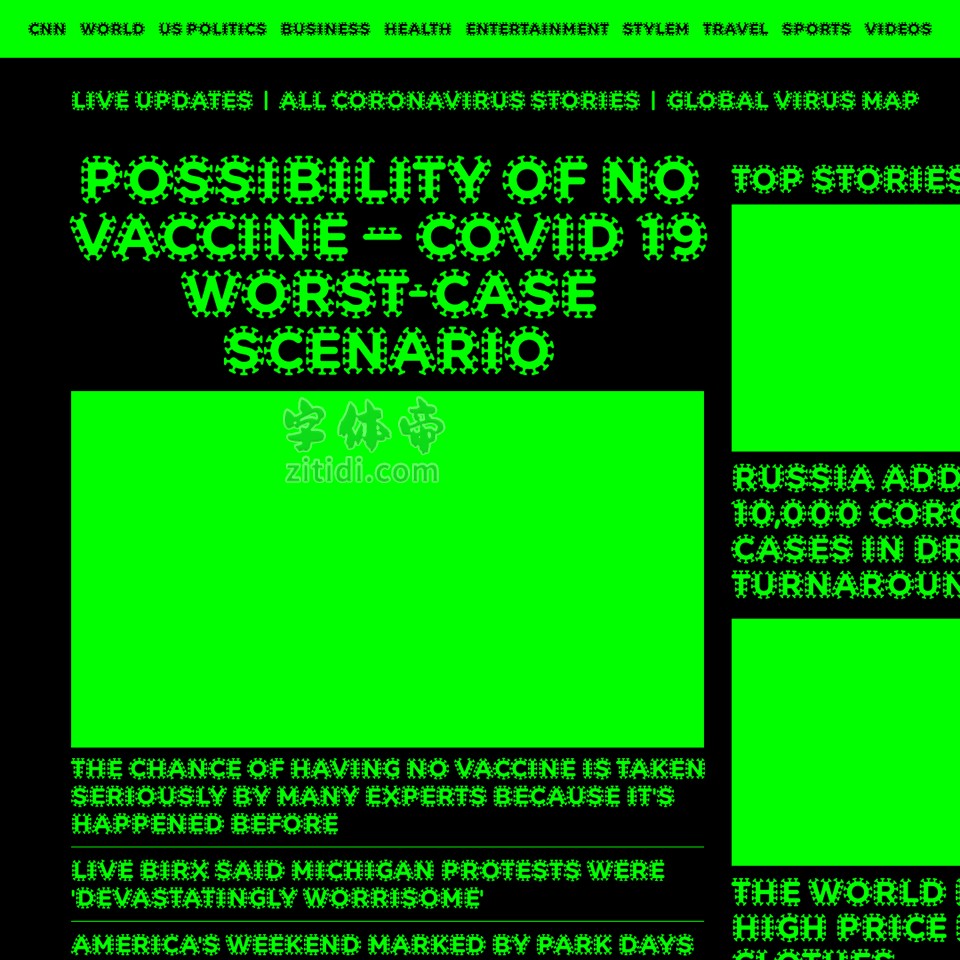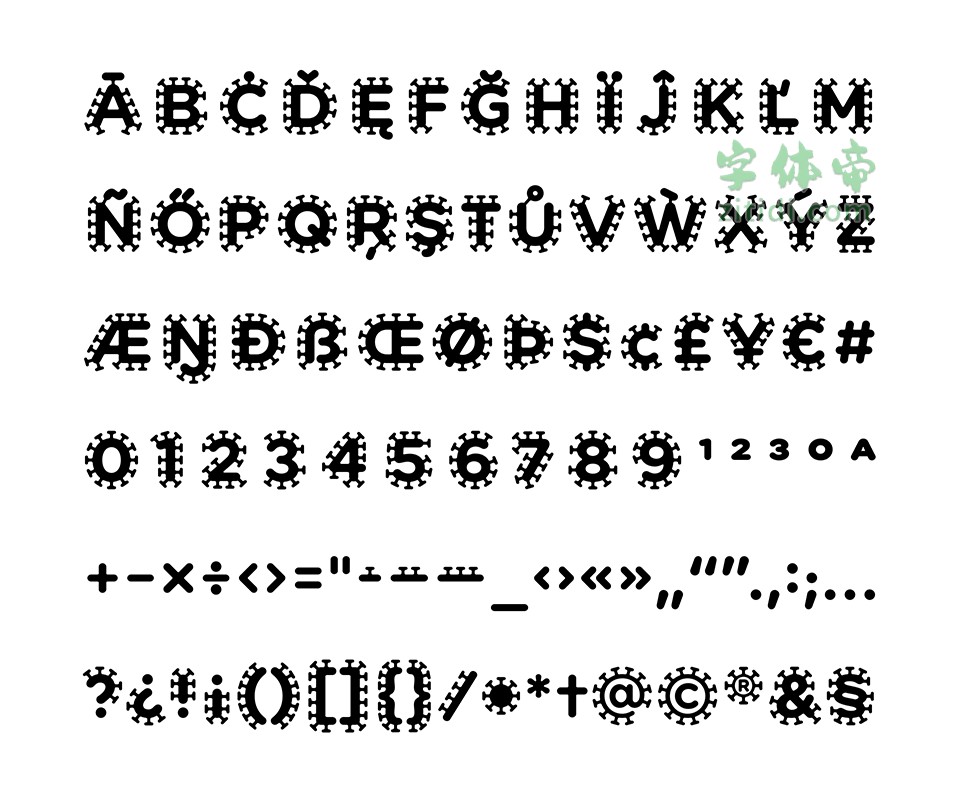
为这些时代引入 Arial。这种字体被简称为 COVID,第一种严重感染的字体现在可供所有人免费使用。首先它接管了我们自己的网站。此外,我们还描绘了关于用漂白剂洗手的指南、在隔离区写的反乌托邦小说、穿山甲的 Zoom 项目和福奇博士的信息图表中的字体。尤其是在宣布大流行结束并在任何地方恢复生命时。更多款式会陆续推出。
“COVID Infected”是一款书写很新颖的字体,字体大方,适合各种设计作品使用!欢迎下载!